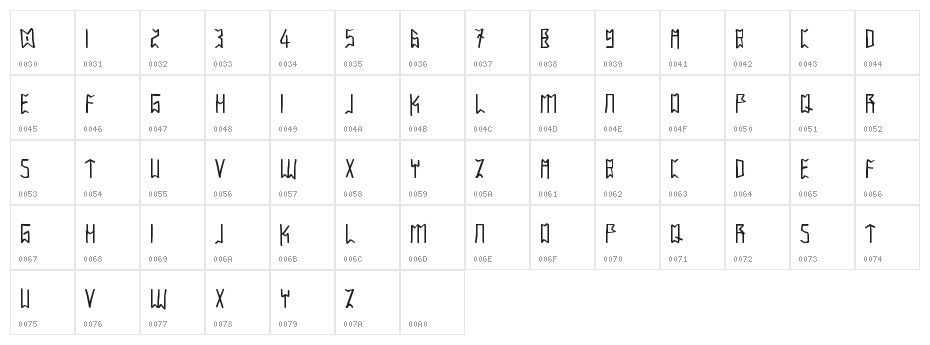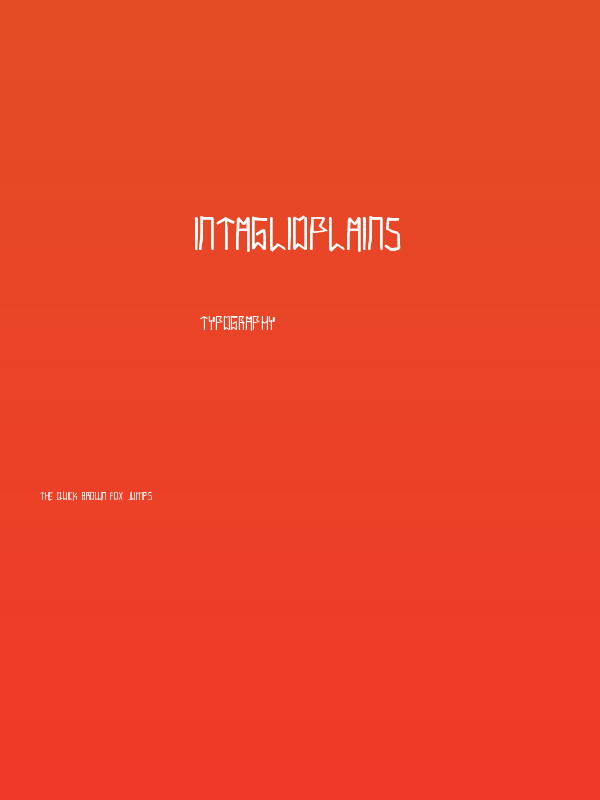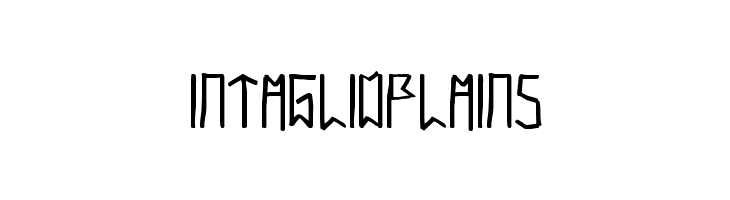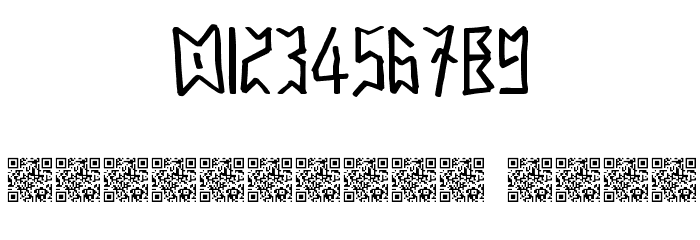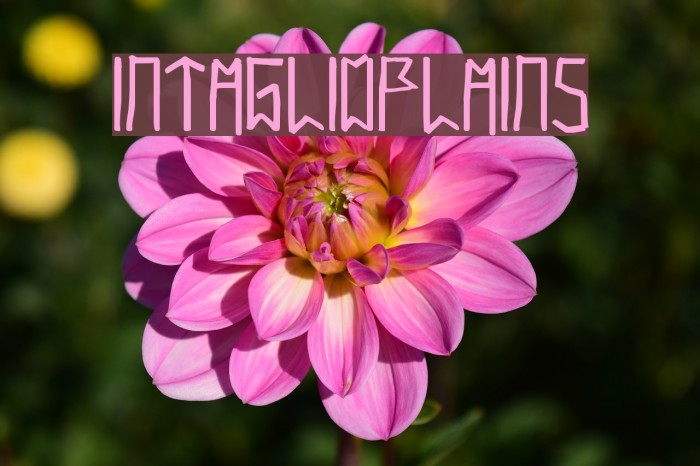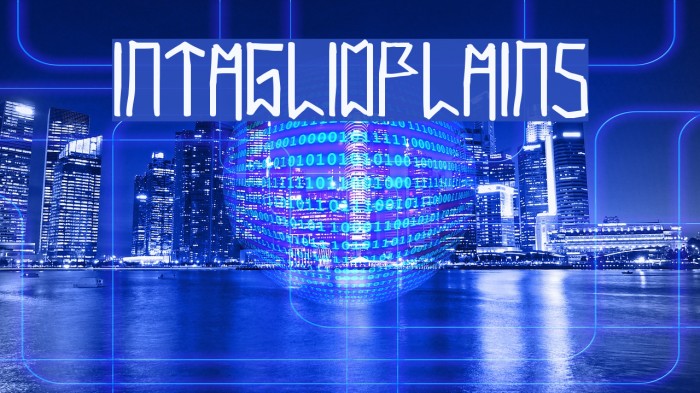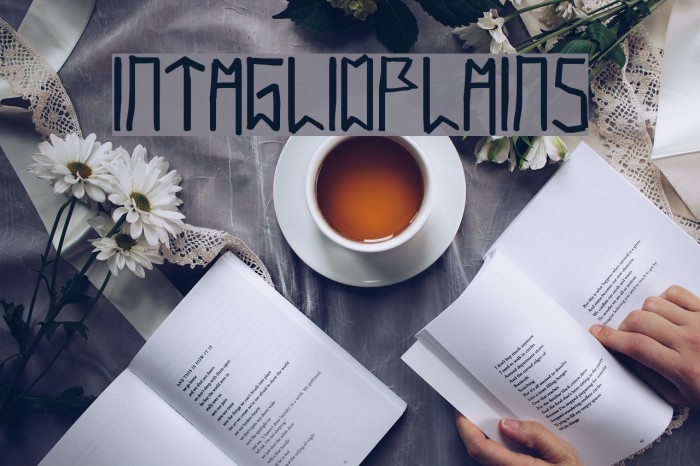
IntaglioPlains Font
✎ Graffiti
| श्रेणियाँ | Graffiti |
| समग्र शैली | Decorative |
| उपयोग का मामला | Headlines, Logos |
| सुझाए गए प्रोजेक्ट | Ideal for fantasy-themed designs, game titles, posters, or branding that requires a mystical or historical touch. |